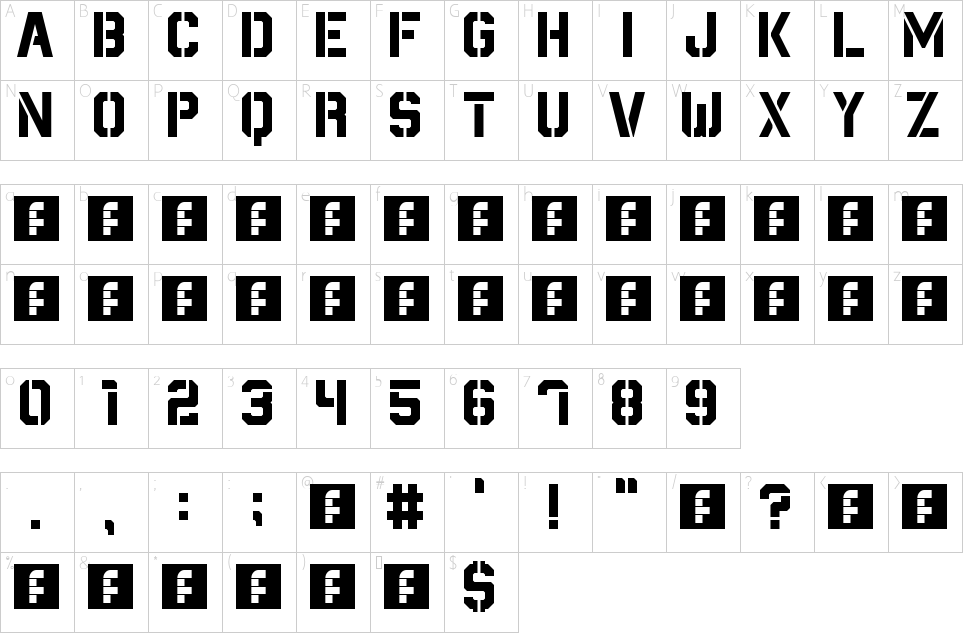
Descubra a força e o poder da Destructive Font com esta categoria de fontes gratuitas para Windows e Mac. Ela foi projetada pela incrível equipe de Geronimo Fonts, que tem conquistado muitos entusiastas do design ao redor do mundo. Até agora, mais de 9.719 pessoas já baixaram esta poderosa ferramenta de escrita para utilizar em seus projetos criativos e pessoais. Se você está procurando por uma fonte que se destaca com suas linhas agressivas e a sua capacidade única de criar um impacto visual, Destructive Font é definitivamente o caminho percorrido. Faça seu design soar mais poderoso e resoluto ao usar esta fonte inovadora em seus próximos trabalhos.